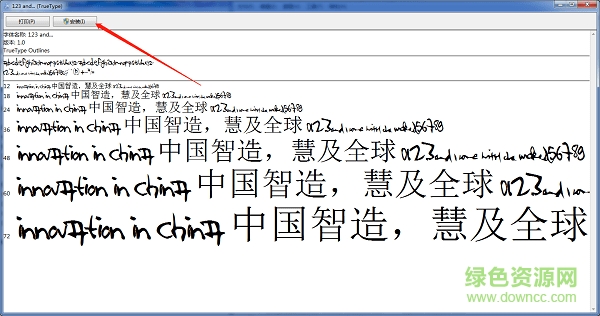
123_and字體
123_and英文字體免費(fèi)版是一款非常有特色的英文字體,整個(gè)字體看起來像少數(shù)民族的字,扭曲的字體形態(tài)搭配各色與眾不同的字體,讓字體整體看起來充滿了藝術(shù)氣息,喜歡的用戶快來綠色資源網(wǎng)下載吧!
123_and字體簡介:
123_and英文字體是一款造型別致的英文字體。這款字體的線條并不流暢,除此之外,它的粗細(xì)也不均勻,整體看起來也是歪歪扭扭的??烧?yàn)橐陨系奶攸c(diǎn)才造成了這款字體的特別,用在設(shè)計(jì)上還是不錯(cuò)的!
123_and英文字體預(yù)覽: